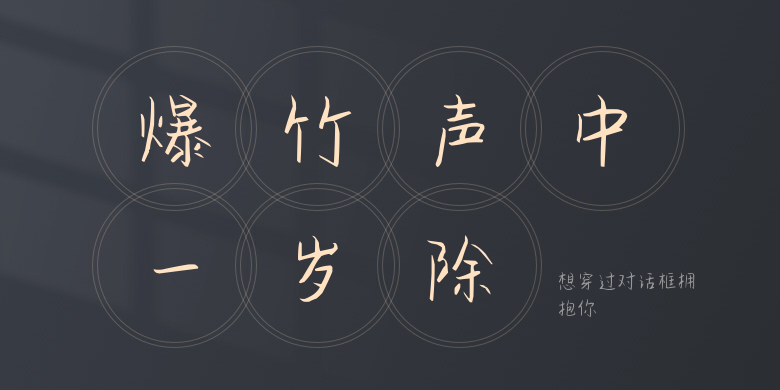
想穿过对话框拥抱你
想穿过对话框拥抱你,这款字体结构工整、笔画清晰,兼顾美观与易读性,适用于标题、正文、海报、包装、LOGO 等多种场景。字形优雅稳定,风格百搭耐看,适配日常排版与创意设计,让文字呈现更舒适、更具质感。想穿过对话框拥抱你一笔一画,皆是细节,以均衡的比例、流畅的线条打造舒适视觉体验,字形端正大气,风格简约现代。无论是商业设计、品牌宣传还是日常排版,都能轻松驾驭,让文字更有格调与力量。想穿过对话框拥抱你字体下载。